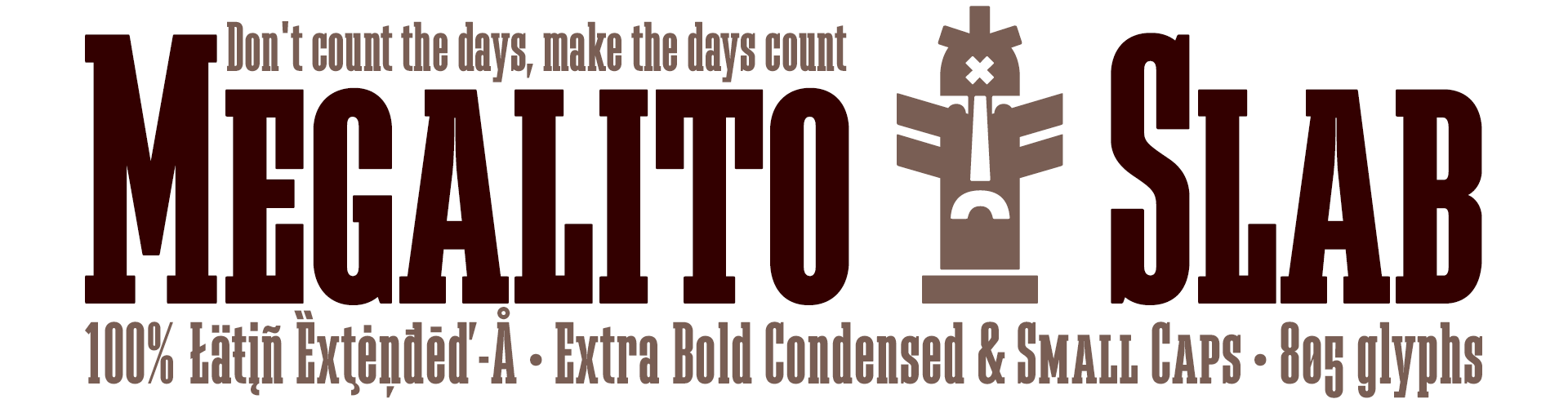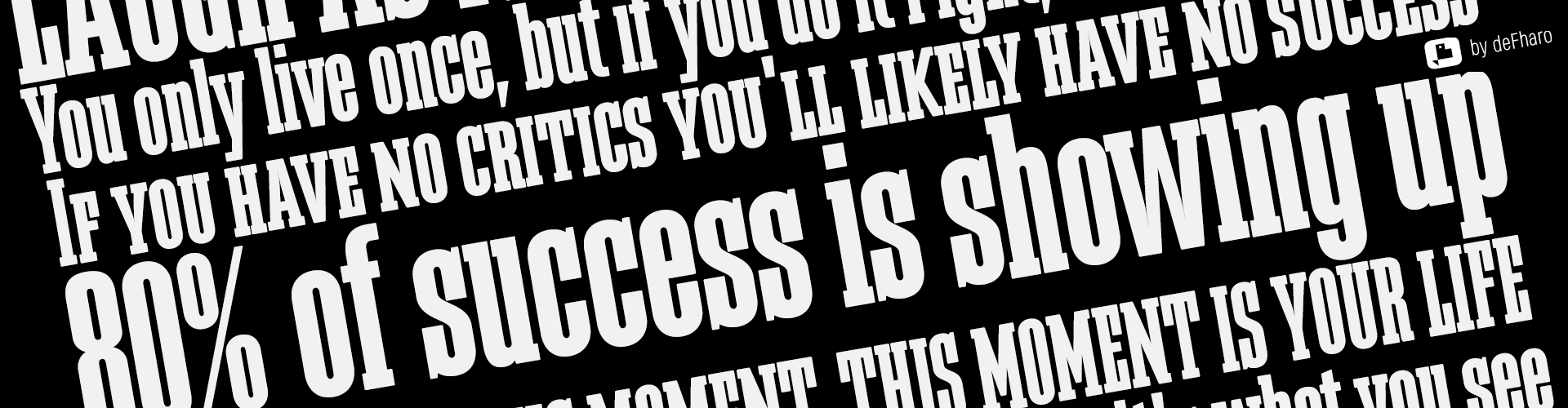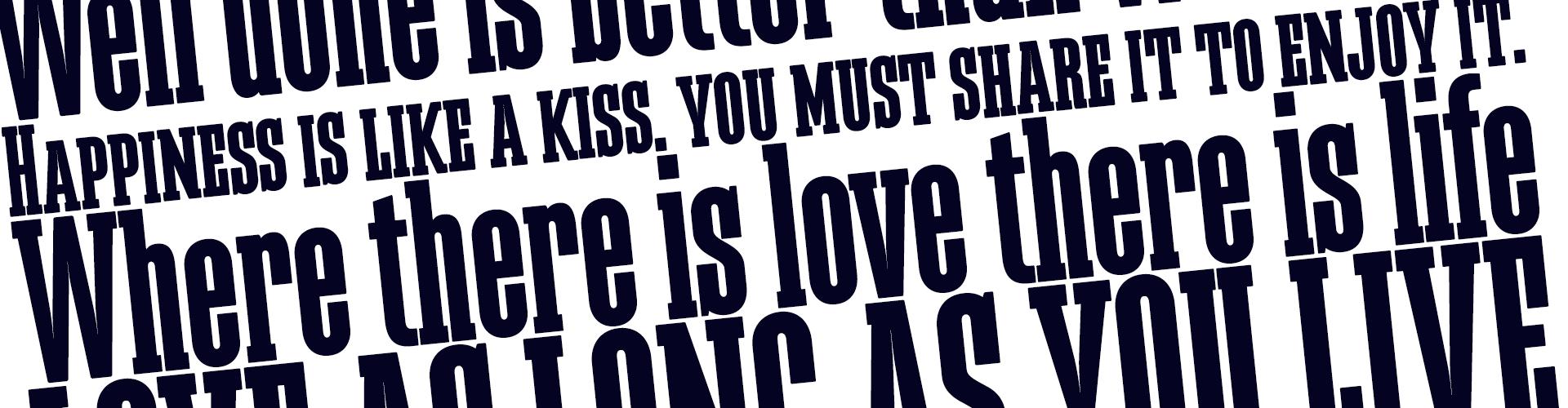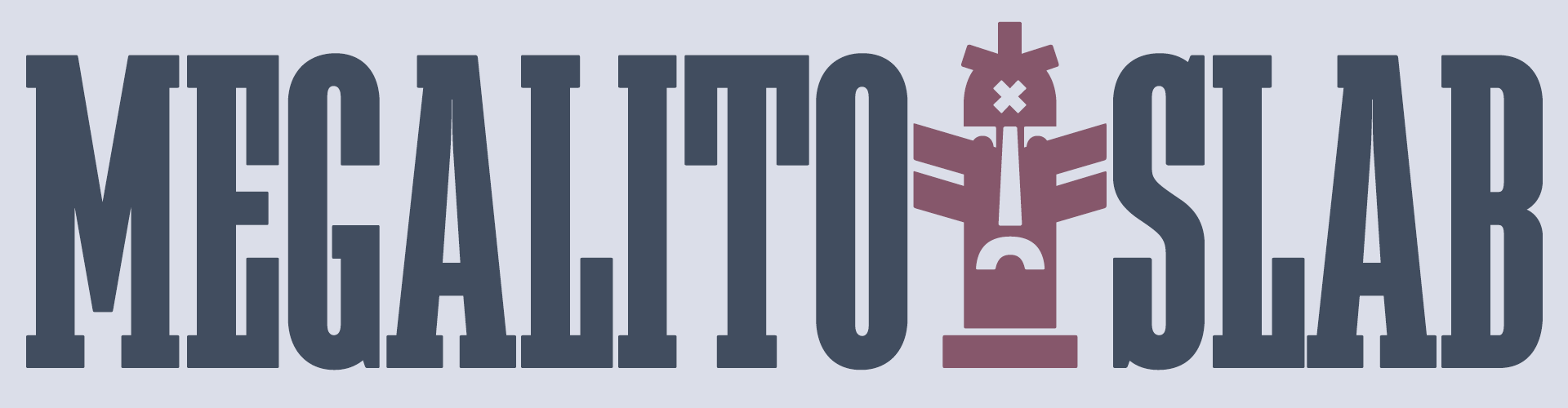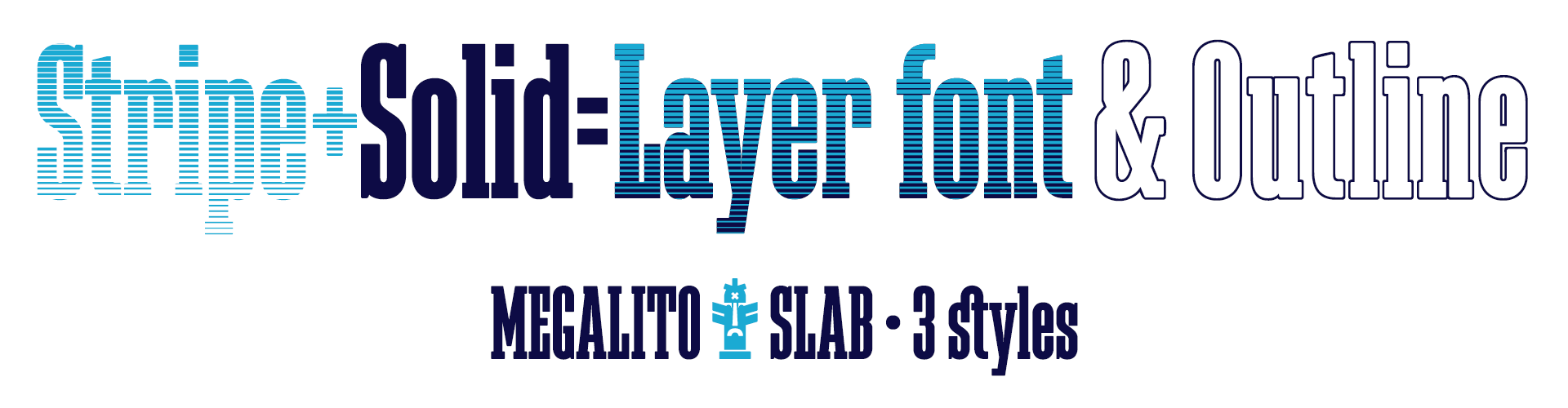
Slab Extra Condensed
Estilo: Slab Serif, Display, Geometric, Outline, Layer Font
Proporción: Extra Condensada
Esta tipografía de estilo Retro nos refiere al diseño de posters, afiches y carteles realizados desde mediados del S.XX hasta hoy. Megalito Slab se presenta en 3 estilos: Slab y Stripe combinables por capas para crear títulos tipográficos multicolores y una versión Outline para uso en grandes titulares.